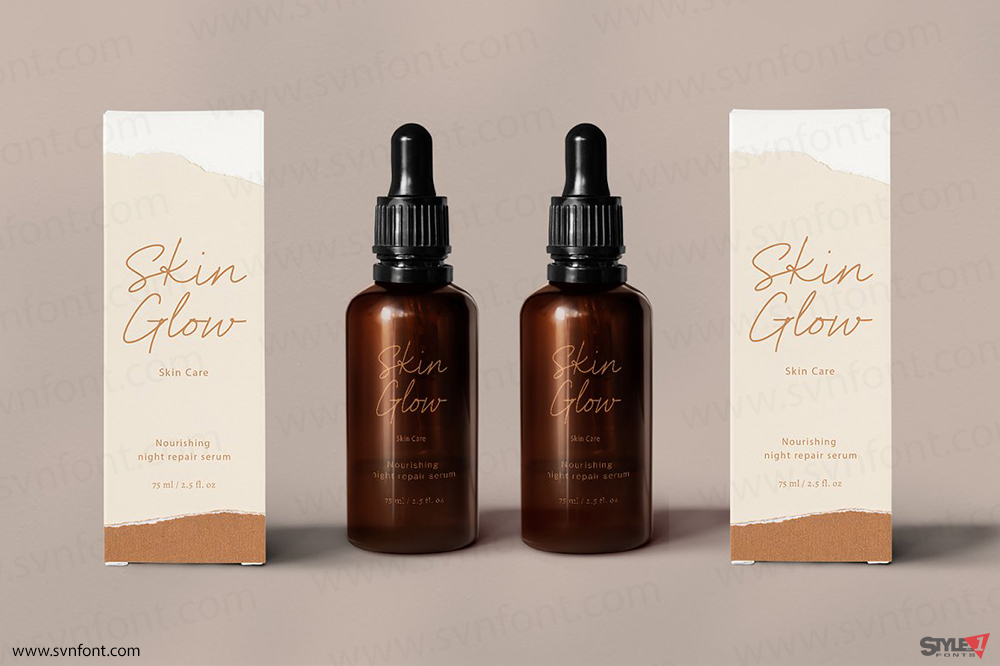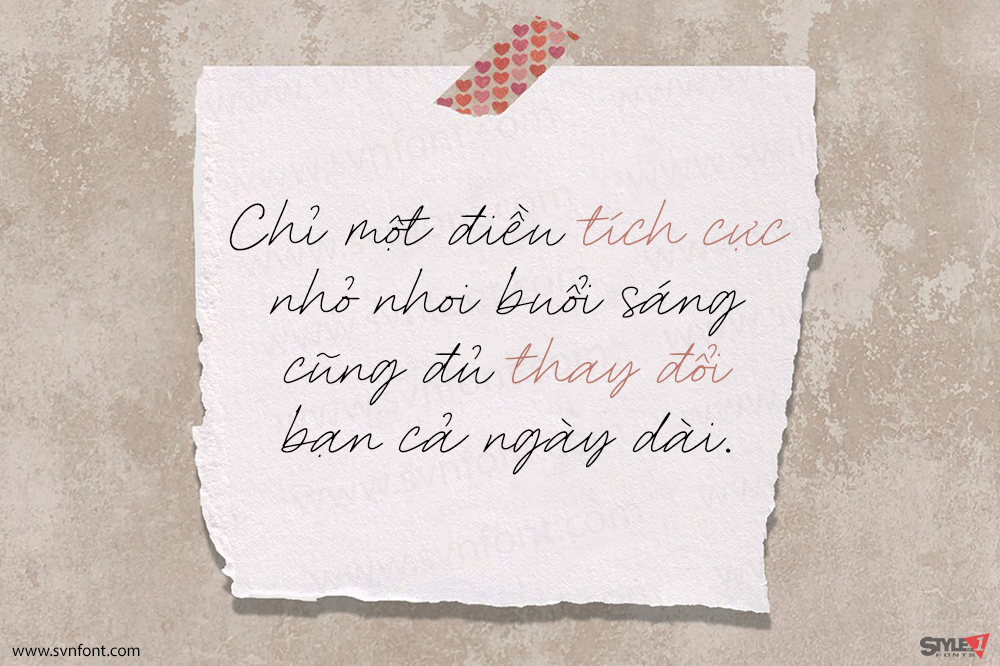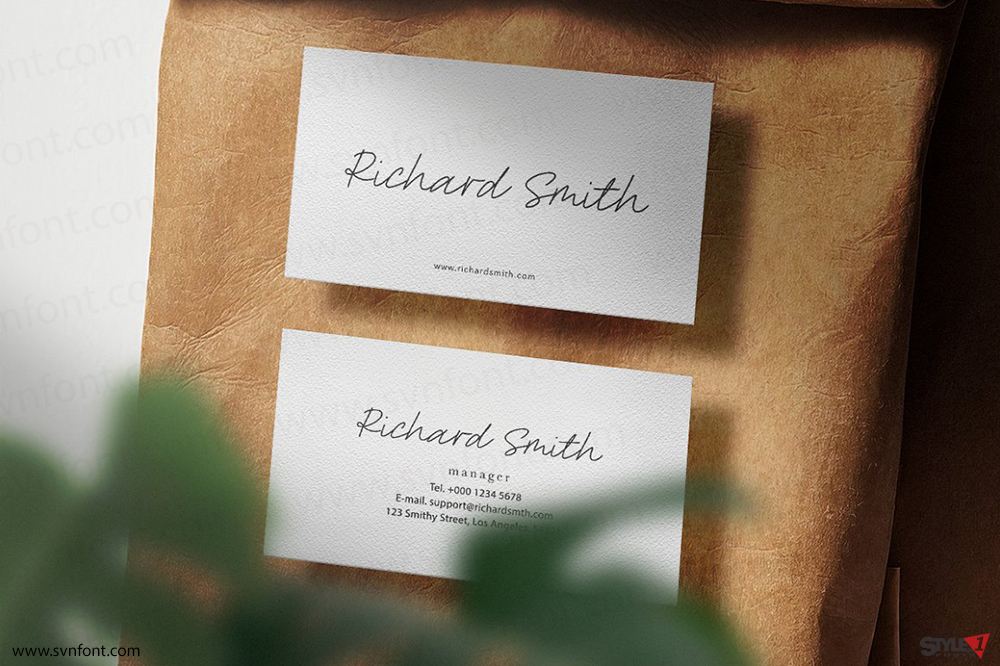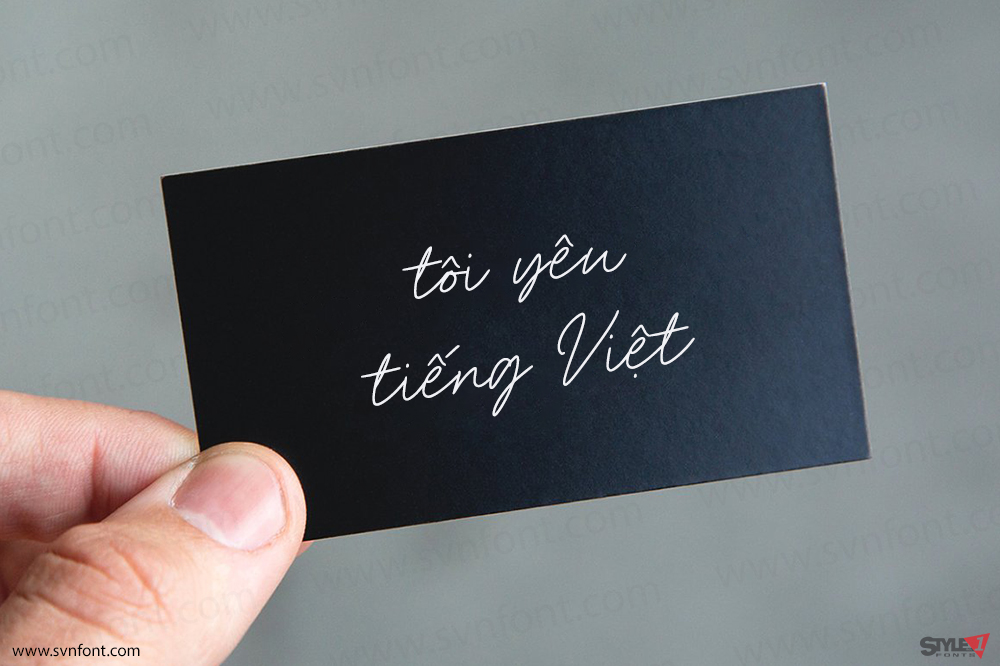
Giới thiệu Authoritative, một phông chữ viết tay tự nhiên, được tạo ra bằng những nét tay tự nhiên, rất phù hợp để bạn sử dụng cho xây dựng thương hiệu, trích dẫn, logo, văn phòng phẩm, đồ thủ công và nhiều mục đích khác.
Nhà thiết kế: Agam Rahmadan
Nhà phát hành: Viswell